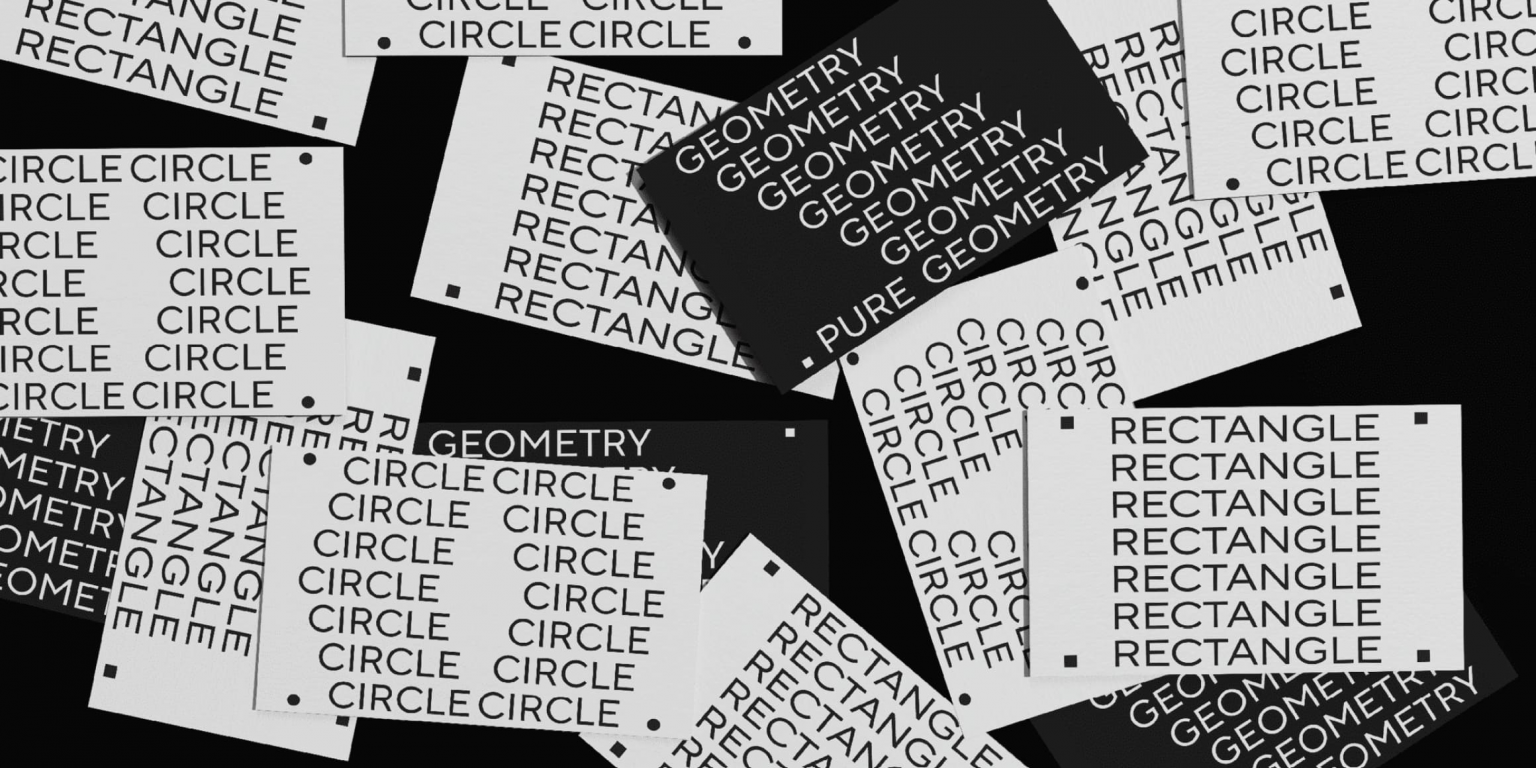
Hai thuật ngữ typeface và font thường bị xem là đồng nghĩa. Tình trạng này không chỉ xuất phát từ sự nhầm lẫn của số đông những người không chuyên, ngay cả trong giới chuyên môn, “font” vẫn thường được dùng thay thế cho cả “typeface” và “font style”. Việc thiếu vắng một hệ thống thuật ngữ thống nhất càng khiến tình hình thêm rối rắm, bởi mỗi nhà thiết kế chữ lại có cách diễn giải riêng.
Bài viết này sẽ phân tích sự khác biệt giữa font và typeface, đồng thời lý giải vì sao việc phân biệt rõ ràng giữa chúng lại quan trọng.
Typeface & Font: Định nghĩa
Typeface là thiết kế tổng thể hoặc phong cách hình ảnh bao quát của một tập hợp ký tự, bao gồm chữ cái, con số và ký hiệu. Nó đại diện cho toàn bộ “gia đình” các font chia sẻ cùng một thẩm mỹ thiết kế. Có thể hình dung typeface như là “bản sắc thị giác” của văn bản giúp định hình diện mạo và cảm xúc của chữ.
Thuật ngữ “typeface” bắt đầu được sử dụng phổ biến trong ngành kiểu chữ từ đầu thế kỷ 20, khi các bộ font mở rộng (extended font families) đầu tiên ra đời do Morris Fuller Benton thiết kế cho xưởng American Type Founders (ATF). Các bộ font này bao gồm nhiều kiểu phông khác nhau về chiều rộng, độ đậm, nhưng thống nhất về thẩm mỹ chung.
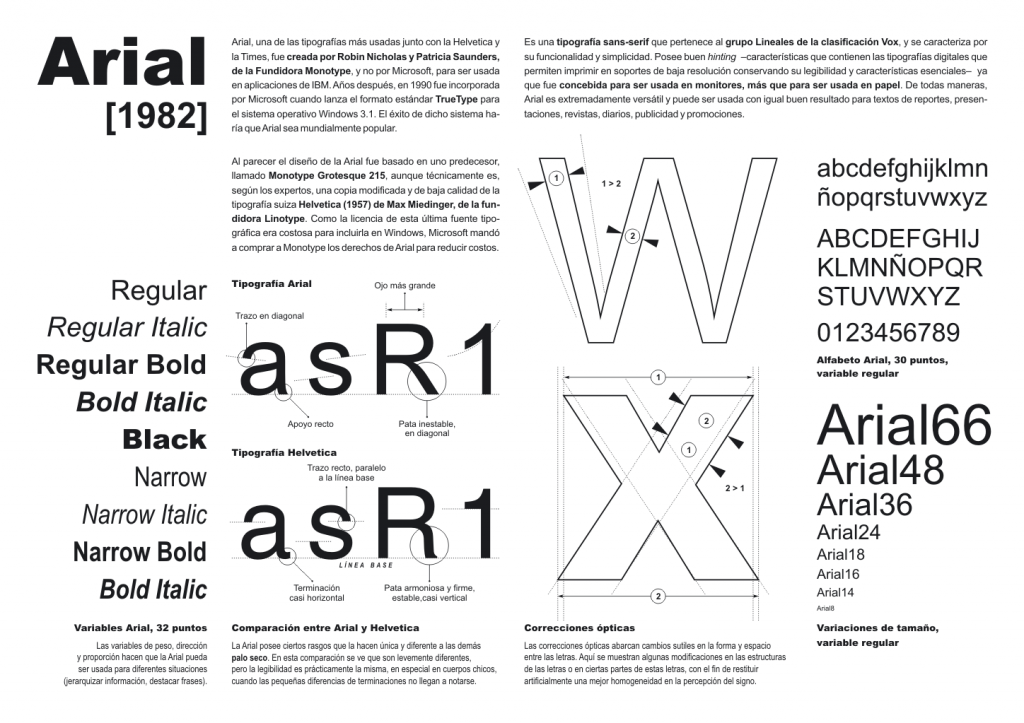
Arial, một kiểu chữ được thiết kế vào năm 1982. Với typeface Arial, một số font phổ biến bao gồm Arial Black, Arial Narrow và Arial Bold.
“Font” là các biến thể cụ thể nằm trong một typeface. Font là một tập hợp ký tự, bao gồm chữ cái, chữ số, dấu câu và các ký hiệu khác được sử dụng trong dàn trang văn bản. Font xác định các thuộc tính như kích cỡ, độ đậm (weight), kiểu dáng (style) và khoảng cách ký tự. Nói cách khác, font chính là cách mà typeface được triển khai trong thực tế.
Trong các hệ typeface hiện đại, các font thậm chí có thể khác biệt đáng kể về mặt hình thái, chỉ cần vẫn nằm trong cùng một ý tưởng thị giác của nhà thiết kế.
Typeface & Type family là gì?
Trước tiên, cần phân biệt hai thuật ngữ “typeface” và “type family” dù chúng có phần giao thoa về nghĩa.
- Type family (hoặc font family): là một hệ thống bao gồm các biến thể của cùng một thiết kế cơ bản. Các font trong hệ này có chung tên gọi và ý tưởng, nhưng có thể khác nhau về mục đích sử dụng, cá tính và phong cách.
- Typeface: có thể dùng để chỉ toàn bộ hệ chữ hoặc một phần trong đó. Trong nhiều tài liệu, “typeface” được xem là từ đồng nghĩa với “type family”.
Tuy nhiên, theo định nghĩa từ từ điển Google Fonts, typeface là thiết kế thị giác cốt lõi có thể được triển khai bằng nhiều công nghệ dàn trang khác nhau và font là một trong các cách triển khai đó.
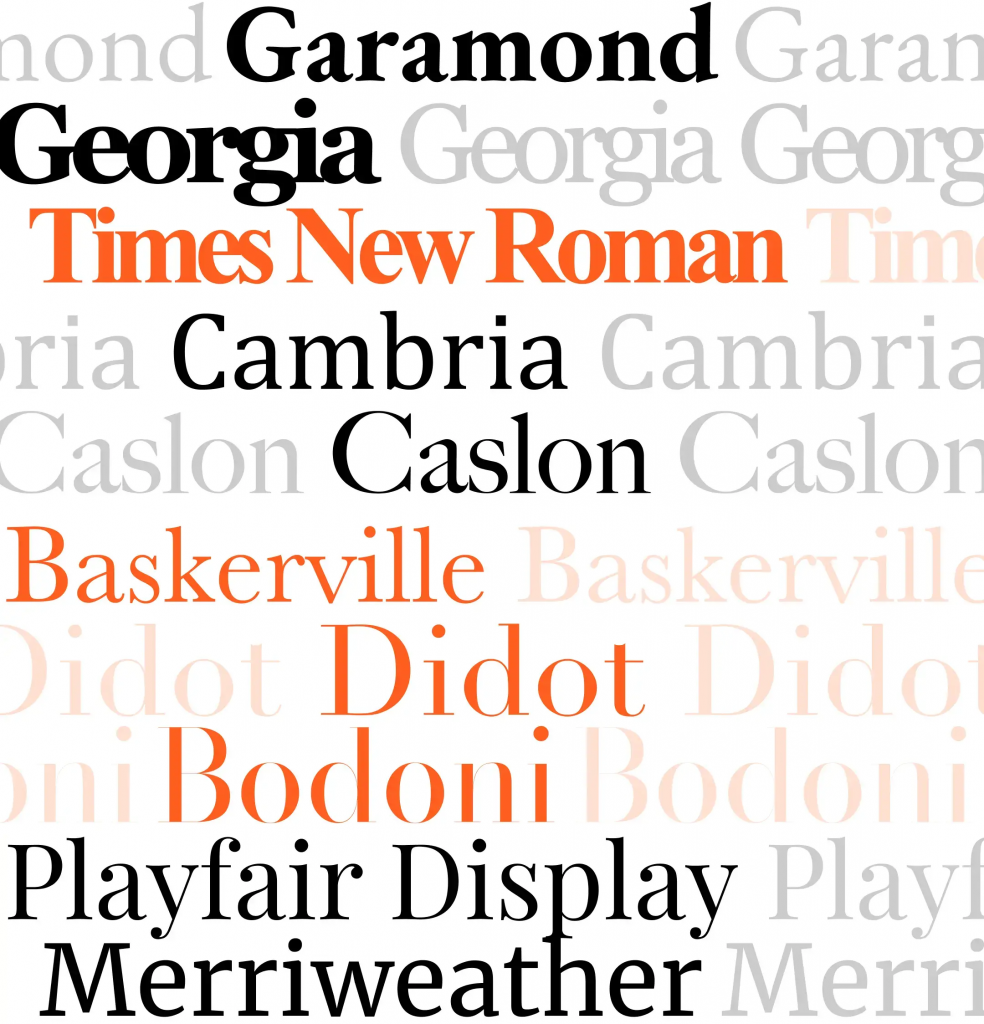
Nói cách khác:
Typeface là thứ bạn “nhìn thấy”, còn font là thứ bạn “sử dụng”.
Trong bối cảnh đó, một lần nữa, khi đề cập đến phân loại font, thực chất chúng ta đang nói đến phân loại typeface.
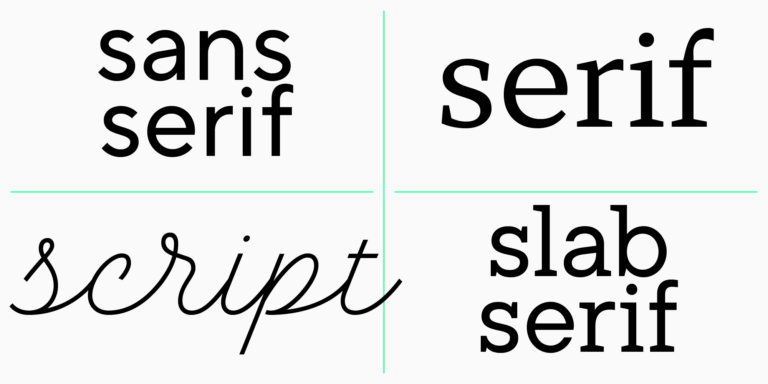
Các loại typeface phổ biến
Hiện không có hệ thống phân loại font hay typeface nào được chuẩn hóa tuyệt đối. Trong bài viết này, chúng ta chỉ đề cập những nhóm cơ bản để giúp phân biệt rõ hơn giữa font và typeface:
- Sans serif (grotesque): Nhóm không có chân chữ, độ tương phản thấp hoặc không có. Ví dụ: TT Commons Pro.
- Serif (antiqua): Nhóm có chân chữ, thường có độ tương phản cao. Ví dụ: TT Ramillas thuộc nhóm Transitional Antiqua.
- Slab serif: Chân chữ dày, hình khối rõ rệt. Ví dụ: TT Rationalist.
- Script: Mô phỏng chữ viết tay. Chúng có thể được xem là typeface nếu có nhiều kiểu font style, nhưng nếu chỉ có một kiểu, thì chúng chỉ là một font. Ví dụ: TT Lovelies Script là một font độc lập.
Font là gì?
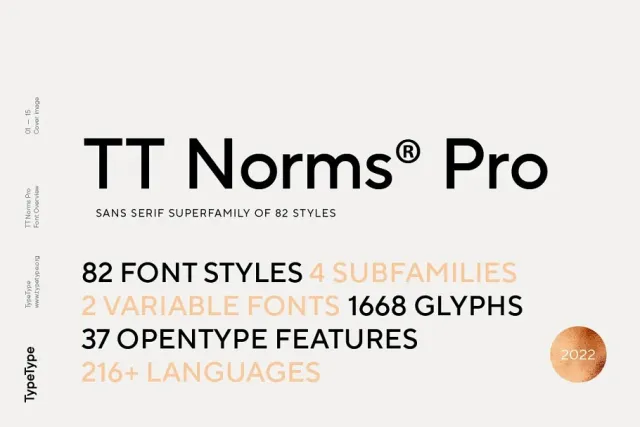
Các loại font (font style) hiện có
Khi nói đến phân loại font, thực chất chủ thể thường là typeface. Vì vậy, chúng ta sẽ bàn sâu hơn về typeface ở phần sau. Trước mắt, hãy tìm hiểu về các kiểu font style:
Font style là biến thể của một font theo độ đậm (weight) và độ nghiêng (slope).
Một font có thể bao gồm cả kiểu đứng (roman) và kiểu nghiêng (italic).
Các mức độ đậm thường được chia thành 3 nhóm chính: Thin, Regular và Bold. Một số kiểu phổ biến nhất gồm: Thin, Regular, DemiBold, Bold. Một số nhà phát triển font mở rộng tập font style thêm các phiên bản như Hairline (siêu mảnh).
Các font có nhiều kiểu font style sẽ được nhóm lại thành một type family (hệ chữ). Và giờ, chúng ta sẽ tìm hiểu về khái niệm này.
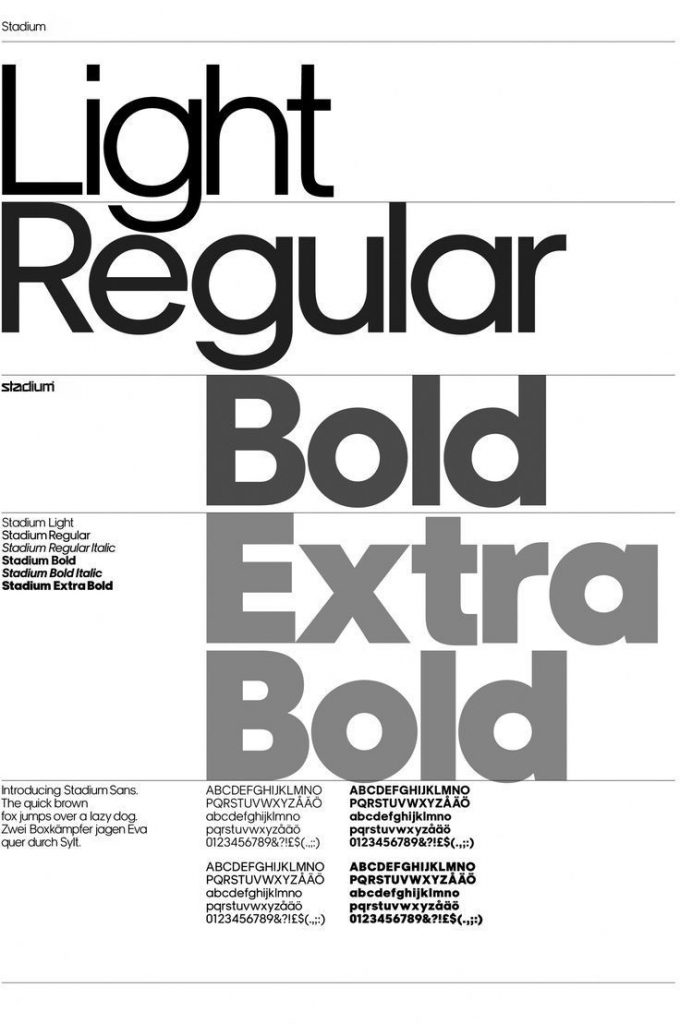
Việc phân biệt Typeface và Font có thực sự quan trọng?
Việc hiểu rõ sự khác biệt giữa font và typeface là điều thiết yếu đối với cả nhà thiết kế lẫn khách hàng. Điều này giúp quá trình làm việc hiệu quả hơn. Việc bạn có nên ưu tiên phân biệt hai khái niệm typeface (kiểu chữ) và font (phông chữ) hay không phụ thuộc vào bối cảnh thiết kế cụ thể của bạn:
Hiểu thuật ngữ không phải là điều kiện bắt buộc để thiết kế tốt:
Dù việc nắm rõ sự khác biệt giữa typeface và font có giá trị nhất định, nhưng nó không quyết định sự thành công của một thiết kế. Nói cách khác, bạn hoàn toàn có thể trở thành một designer giỏi mà không cần phân biệt kỹ lưỡng giữa hai khái niệm này.
Ưu tiên bố cục chữ (typography) trong thiết kế quan trọng hơn việc đúng từ ngữ:
Việc lựa chọn typeface và font phù hợp, cùng với các yếu tố như khoảng cách chữ, nhịp điệu và hệ thống phân cấp thị giác, sẽ ảnh hưởng trực tiếp đến trải nghiệm người dùng và hiệu quả truyền tải thông điệp hơn là việc dùng đúng thuật ngữ.
Biết một chút từ vựng chuyên ngành sẽ hữu ích, nhưng không phải là tất cả:
Cuối cùng, điều quan trọng nhất vẫn là hiệu quả thị giác của thiết kế—liệu nó có truyền đạt đúng thông điệp, đúng cảm xúc, và dễ tiếp nhận hay không.